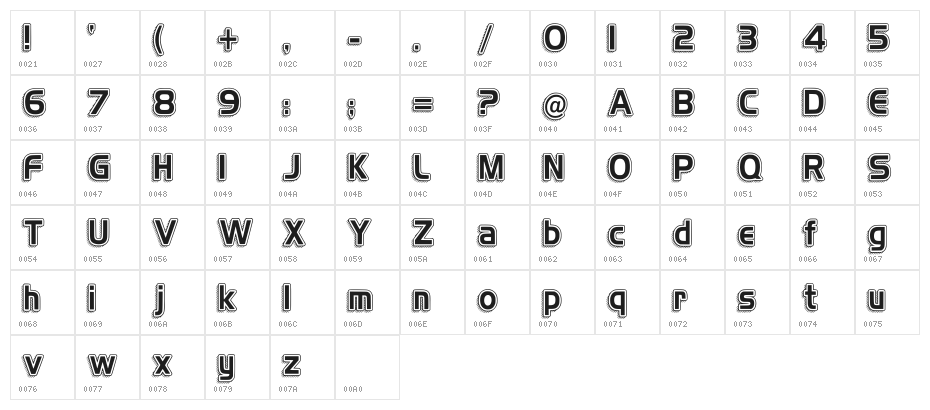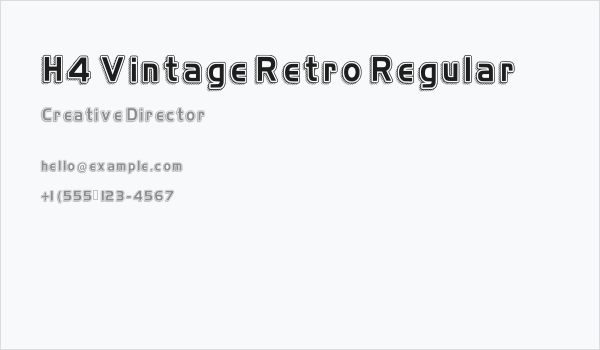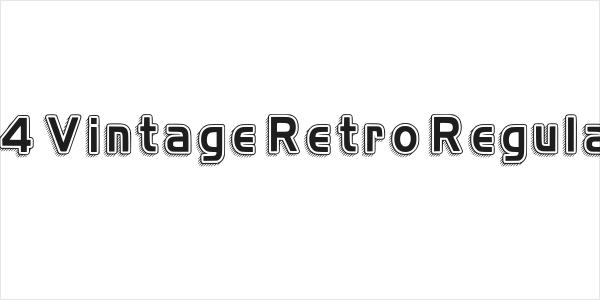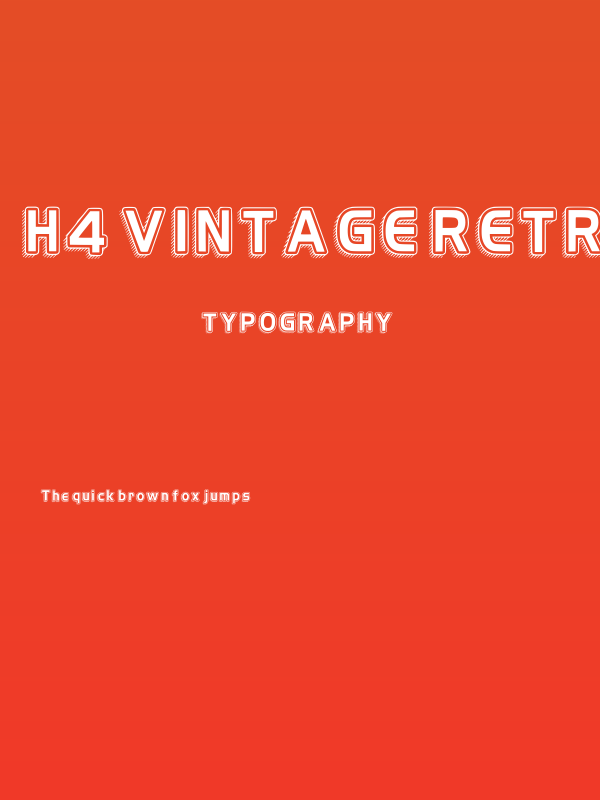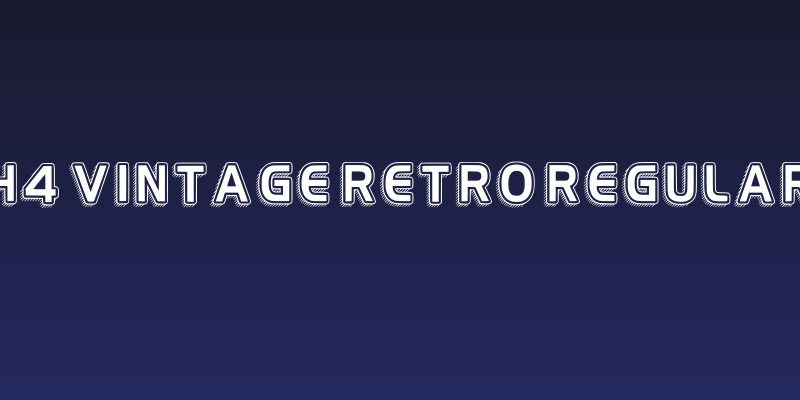
H4 Vintage Retro Regular Font
Hardik
| Progetti proposti | Perfect for retro-themed posters, vintage branding, eye-catching headlines, and creative logos. |